Tipografía vasca: la historia de una grafía tradicional
Probablemente la hayas visto en algún lugar y ya hayas sabido distinguir cuál es. Se trata de la tipografía vasca, una grafía muy característica que se inspiró en los signos alfabéticos de las tumbas vascas y que todavía puede encontrarse en los cementerios del País Vasco ultrapirenaico y en las montañas de Navarra.
Los primero ejemplos se encontraron en la Edad Media pero todavía hoy, mucho más estandarizadas y convertidas en un símbolo de la región sirven hasta para las placas de las calles o los rótulos de una taberna.
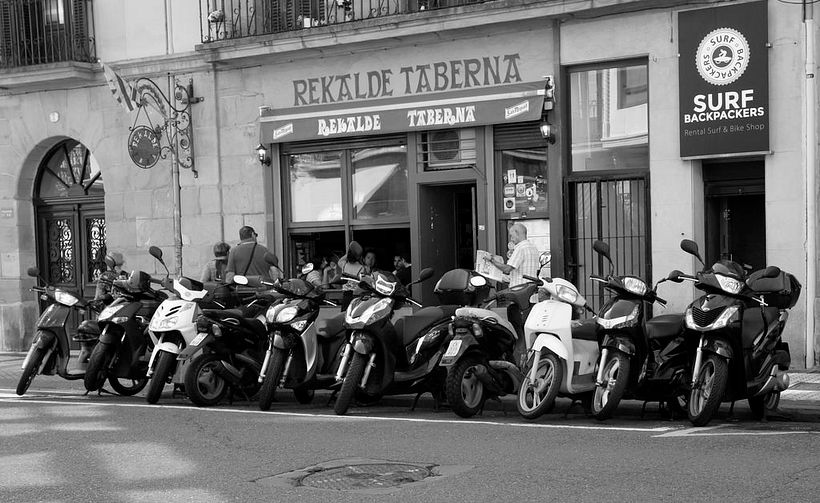
Su evolución hasta la actualidad es el resultado de la transmisión visual y familiar, como otros símbolos de la idiosincrasia vasca como las danzas, la pelota vasca o el levantamiento de piedras. La letra vasca es, en origen, una interpretación de la escritura románica pues se parecía bastante a la de las iglesias románicas, y como solo se usaba en inscripciones al principio solo existían los caracteres en mayúsculas.
Las que conocemos actualmente son variaciones e interpretaciones de la original que acabaron de consolidarse a principios del siglo XX con el llamado Renacimiento Vasco (Euzko Pizkundea) un movimiento cultural con el que se empezó a recuperar y conservar la cultura vasca. Un periodo que quedó congelado durante la dictadura franquista, pero que al concluirse volvió a ganar impulso.
Convertido en un símbolo folclórico que el pueblo vasco ha sabido proteger y trasladar al presente, esta tipografía ha conseguido convertirse en una marca de la región que puede ser fácilmente identificable. Más allá de las consideraciones políticas, proteger una grafía a lo largo de los siglos es un abrazo a la cultura tipográfica.
Ya con sus propias minúsculas y una variedad asombrosa de grafías, la tipografía vasca es difícil de concretar en una sola. Aquí os dejamos algunas de descarga gratuita para que podáis conocerlas y probarlas más de cerca.